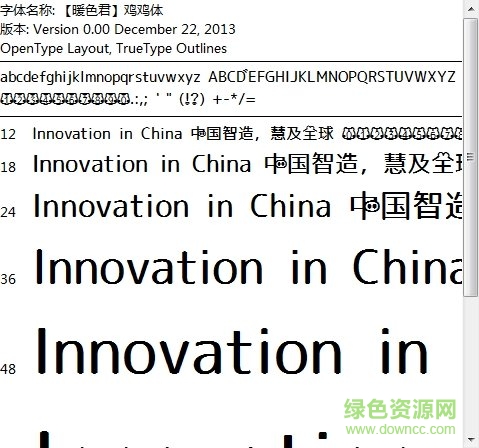
男朋友ttf字體是暖色君新浪微博分享的一款特色字體,是一款有著各種干凈純粹的的手寫字體,讓你的文字顯得更加活潑,給人比較有趣的視覺閱讀體驗(yàn),綠色資源網(wǎng)誠意推薦!
暖色君的男朋友字體是支持蘋果手機(jī)、蘋果電腦、安卓手機(jī)等使用的中文字體,原名暖色君的雞雞體,該字體造形奇特,效果特殊,適用于產(chǎn)品設(shè)計(jì)、包裝印刷、報(bào)刊雜志、繪畫創(chuàng)作等方面。